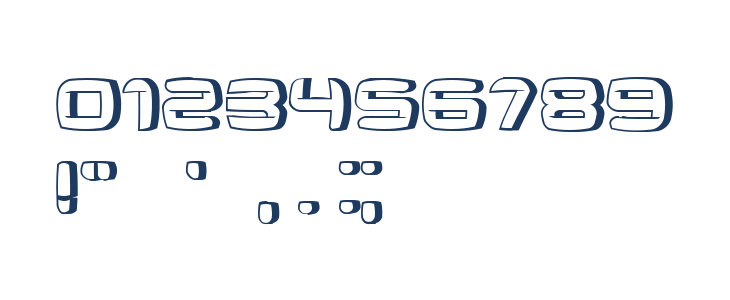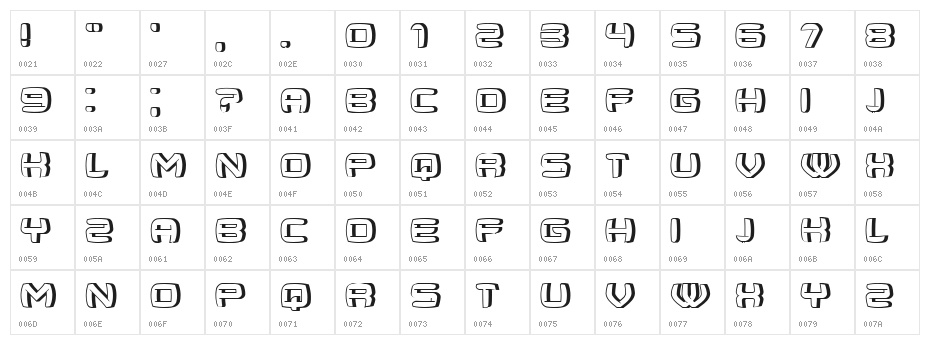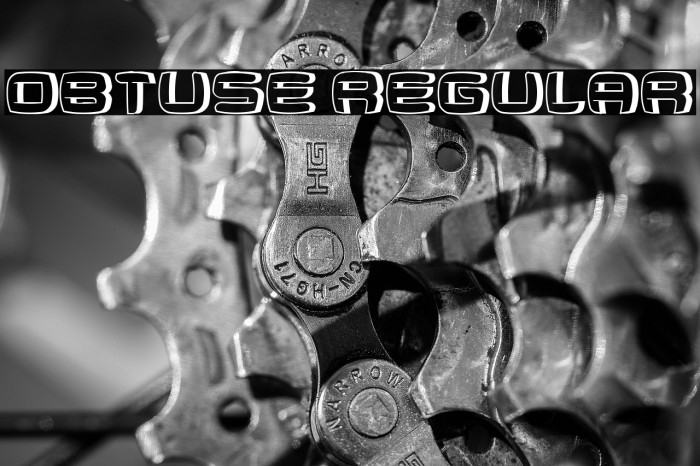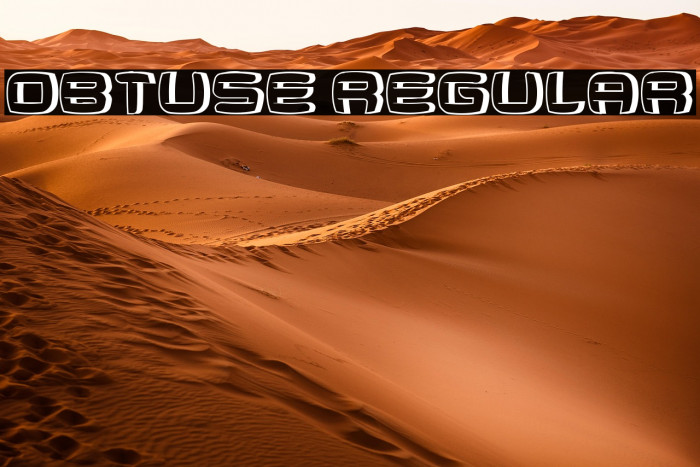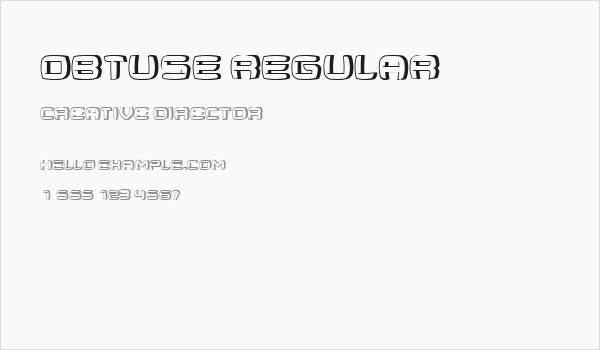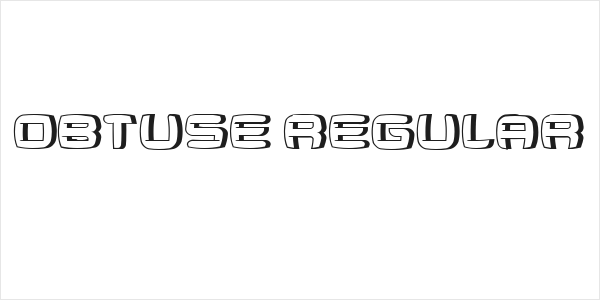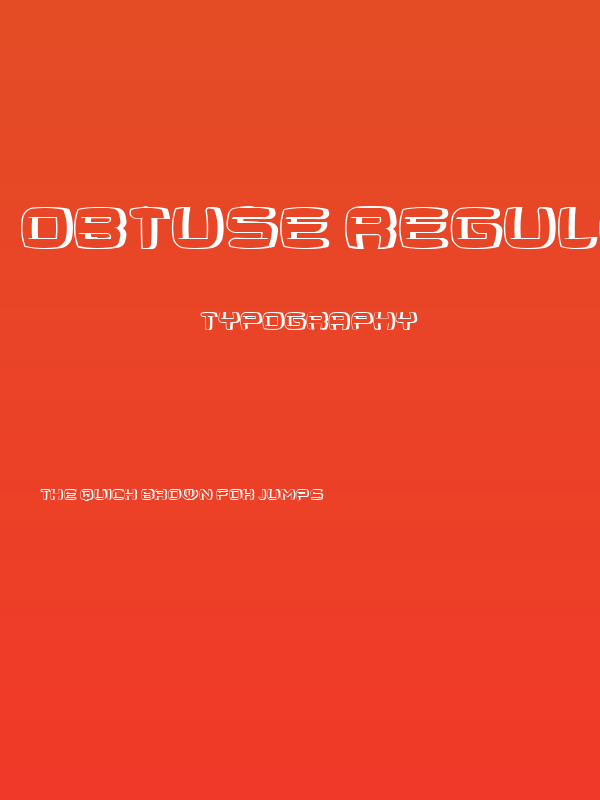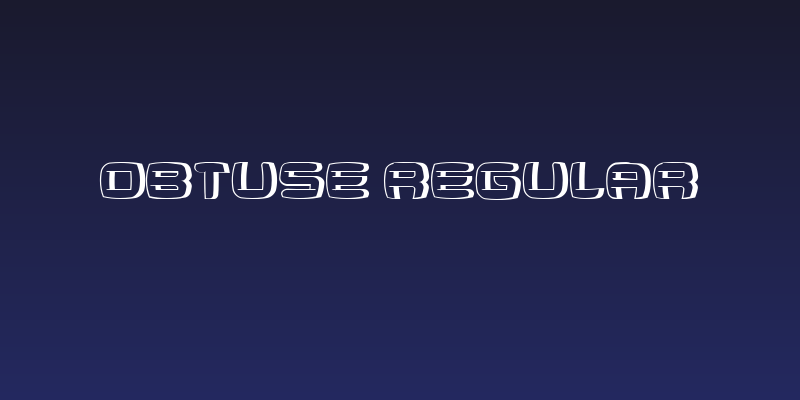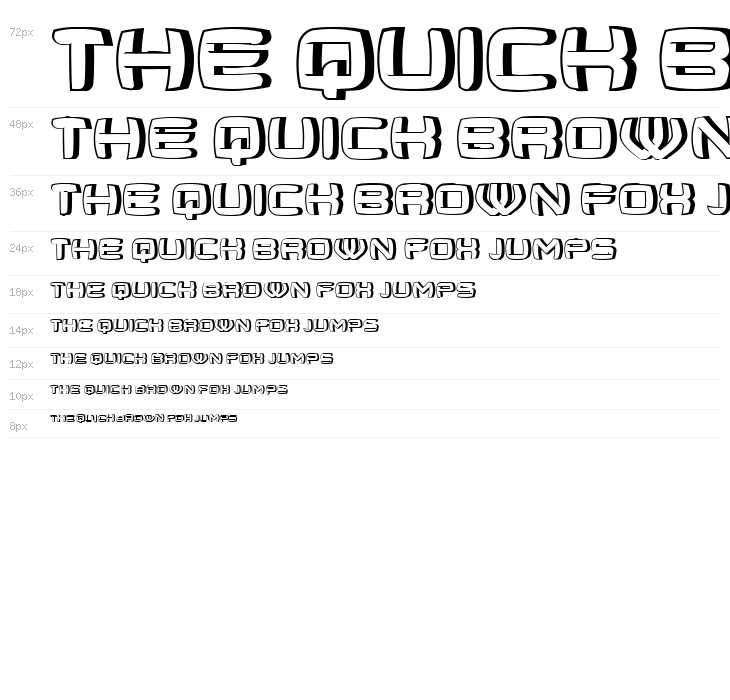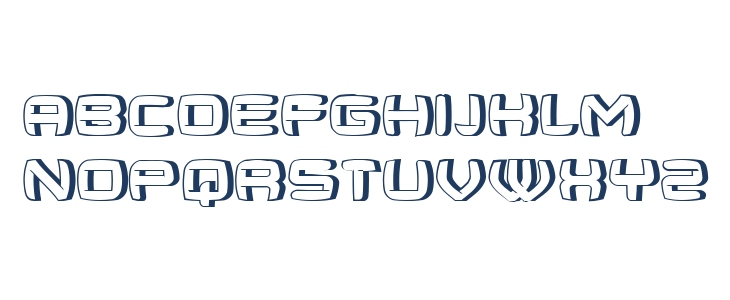
Obtuse Regular Font
| Larghezza | Expanded |
| Stile generale | Futuristic, Modern |
| Progetti proposti | Ideal for sci-fi themed designs, video game graphics, posters, and branding that requires a modern and bold aesthetic. |